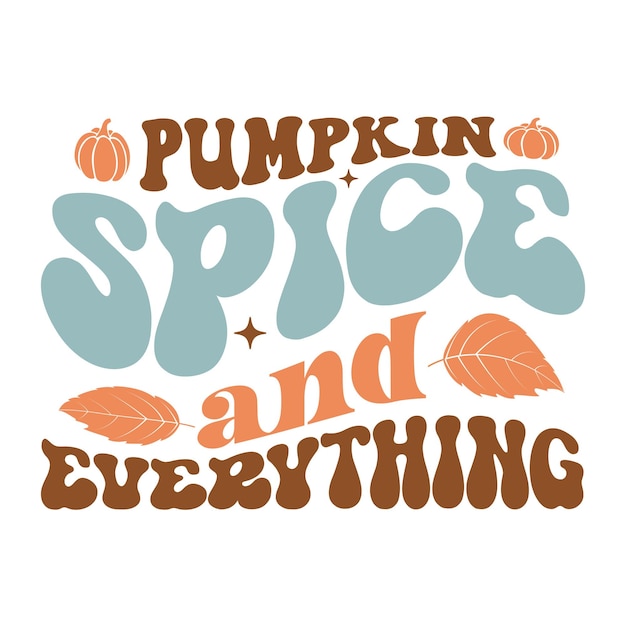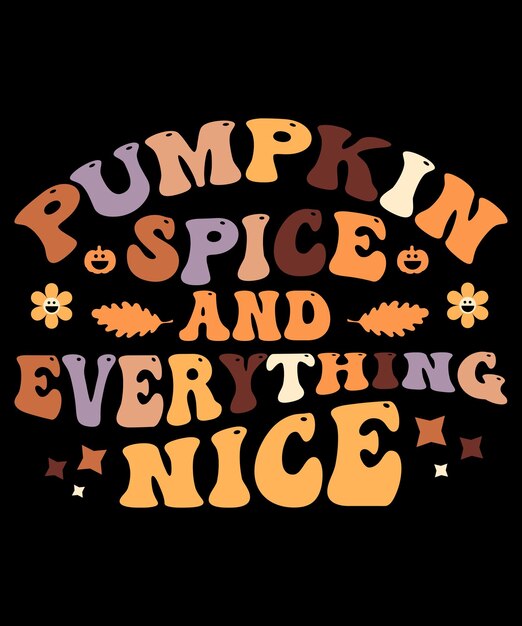
lettrage d'automne et d'automne, t-shirt vintage de typographie groovy dessiné à la main isolé d'automne et d'automne.
Lettrage d'automne et d'automne, t-shirt vintage de typographie groovy dessiné à la main isolé d'automne et d'automne.